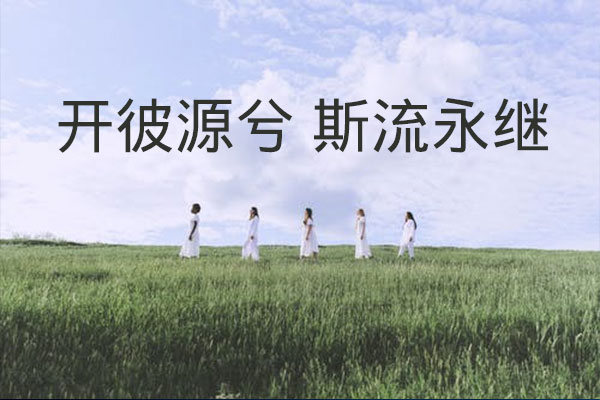
文泉驿微米黑(WenQuanYi Micro Hei)是由学者房骞骞于2004年发起的公益项目——文泉驿的一部分。文泉驿微米黑是一款“自由字体”,其包含常用简体中文、繁体中文所需的汉字(最新版本已覆盖超过20,932个汉字,全面覆盖GB2312、Big5以及GBK标准字符集)。此外,该字体还融入了日文、韩文以及其他几十种语言符号。不仅如此,它还引入了高质量的Droid Sans拉丁符号和Droid Sans Mono等宽字体,同时内置了Hinting和Kerning信息。
微米黑字体文件精简至极,使其在便携式电脑设备上表现卓越。该字体提供粗细两个版本:等宽微米黑和细微米黑,以适应不同的设计需求。
房骞骞发起的这个公益项目的初衷是改善当时高质量中文字体匮乏的情形,以适应Linux系统开发。尽管该字体已经停止更新,并没有更多的免费新字体出现,但其为开源字体领域做出的贡献不容忽视。